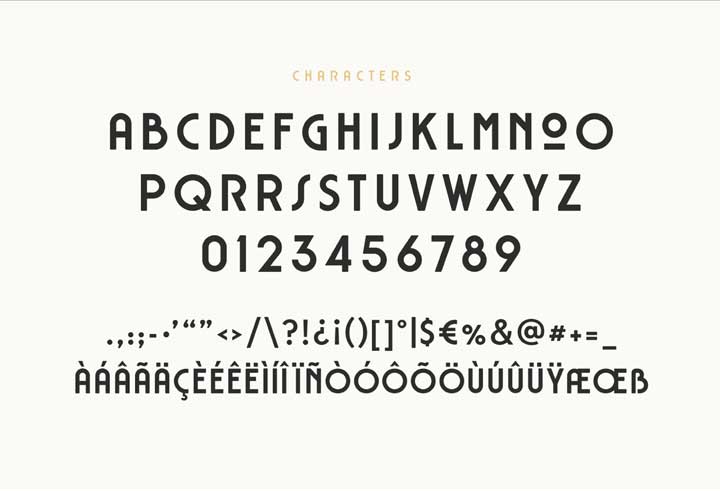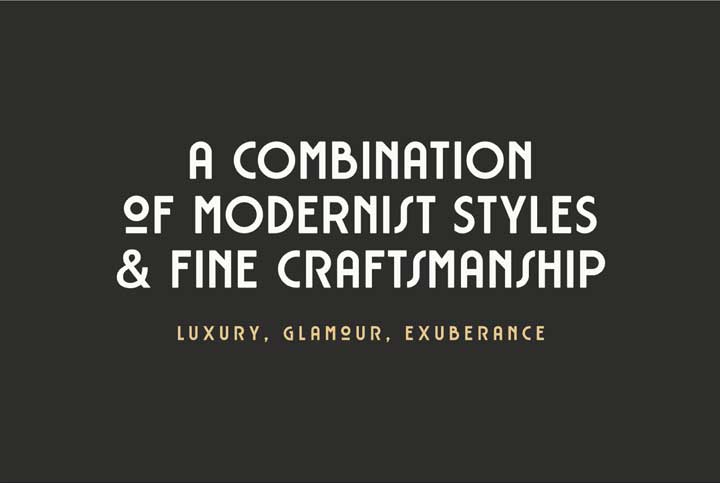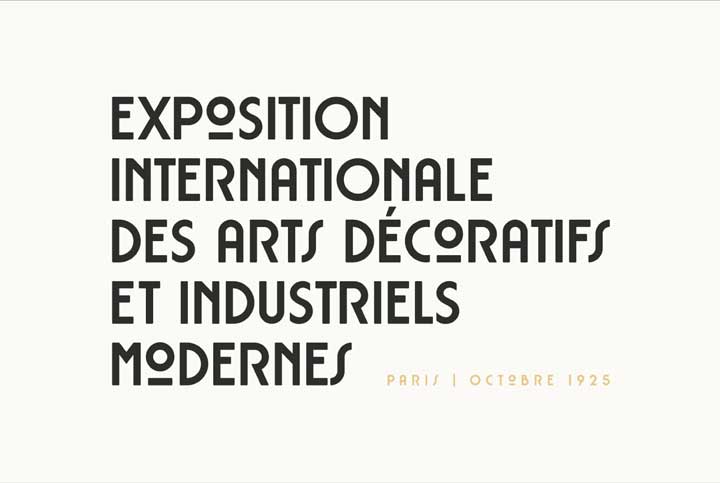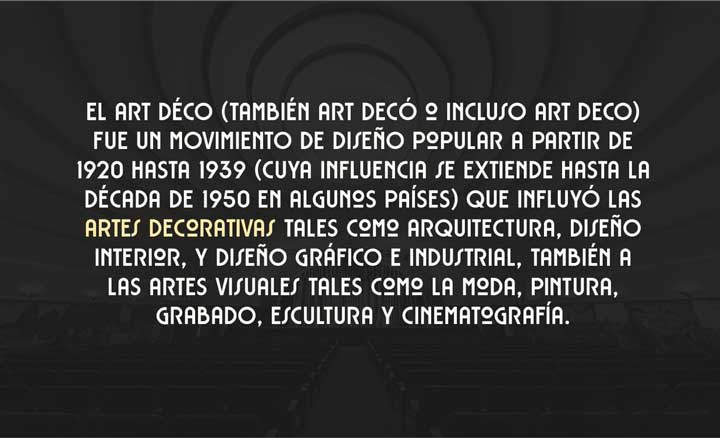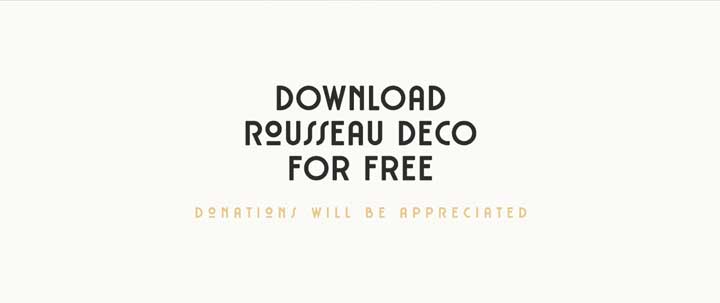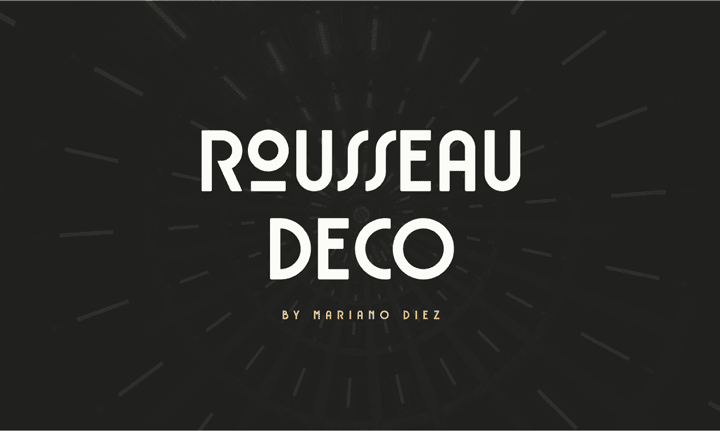
Rousseau Deco: Sebuah Pilihan Tipografi
Rousseau Deco adalah font sans-serif yang terinspirasi dari estetika Art Deco, hasil karya desainer berbakat Mariano Diez. Dengan ciri khas garis-garis tegas dan geometri yang elegan, Rousseau Deco mampu menghadirkan sentuhan vintage yang memikat pada setiap proyek desain Anda.
Keunggulan Rousseau Deco font terletak pada versatilitasnya. Font ini dapat digunakan sebagai elemen utama (standalone) dalam sebuah desain, atau dipadukan dengan karakter huruf lainnya untuk menciptakan komposisi tipografi yang lebih kompleks dan menarik. Kesederhanaan desain sans-serif memungkinkan Rousseau Deco mudah dibaca dan dipahami, sehingga cocok untuk berbagai aplikasi, mulai dari desain logo, poster, hingga konten digital.
Dengan Rousseau Deco, Anda dapat menambahkan sentuhan elegan dan retro pada karya-karya Anda tanpa harus merogoh kocek lebih dalam. Jadi, manfaatkan kesempatan ini dan ciptakan desain yang memukau dengan bantuan Rousseau Deco!
Karya Mariano Diez tidak hanya menyediakan solusi tipografi yang menarik secara visual, tetapi juga mendemokratisasi akses ke sumber daya desain berkualitas tinggi. Rousseau Deco font menjadi bukti kekuatan font sumber terbuka dalam menumbuhkan kreativitas dan memungkinkan desainer untuk membuat narasi visual yang berdampak.